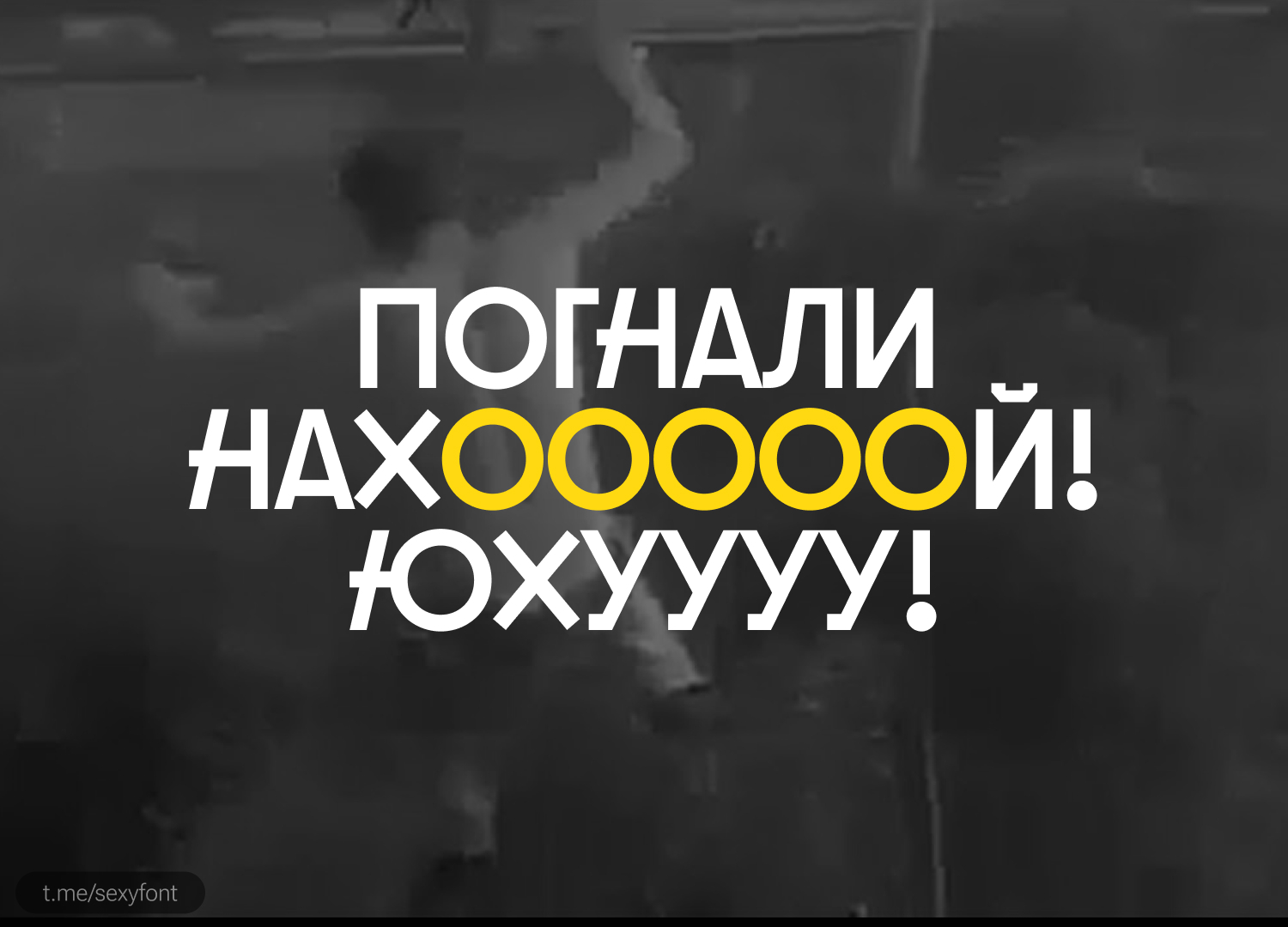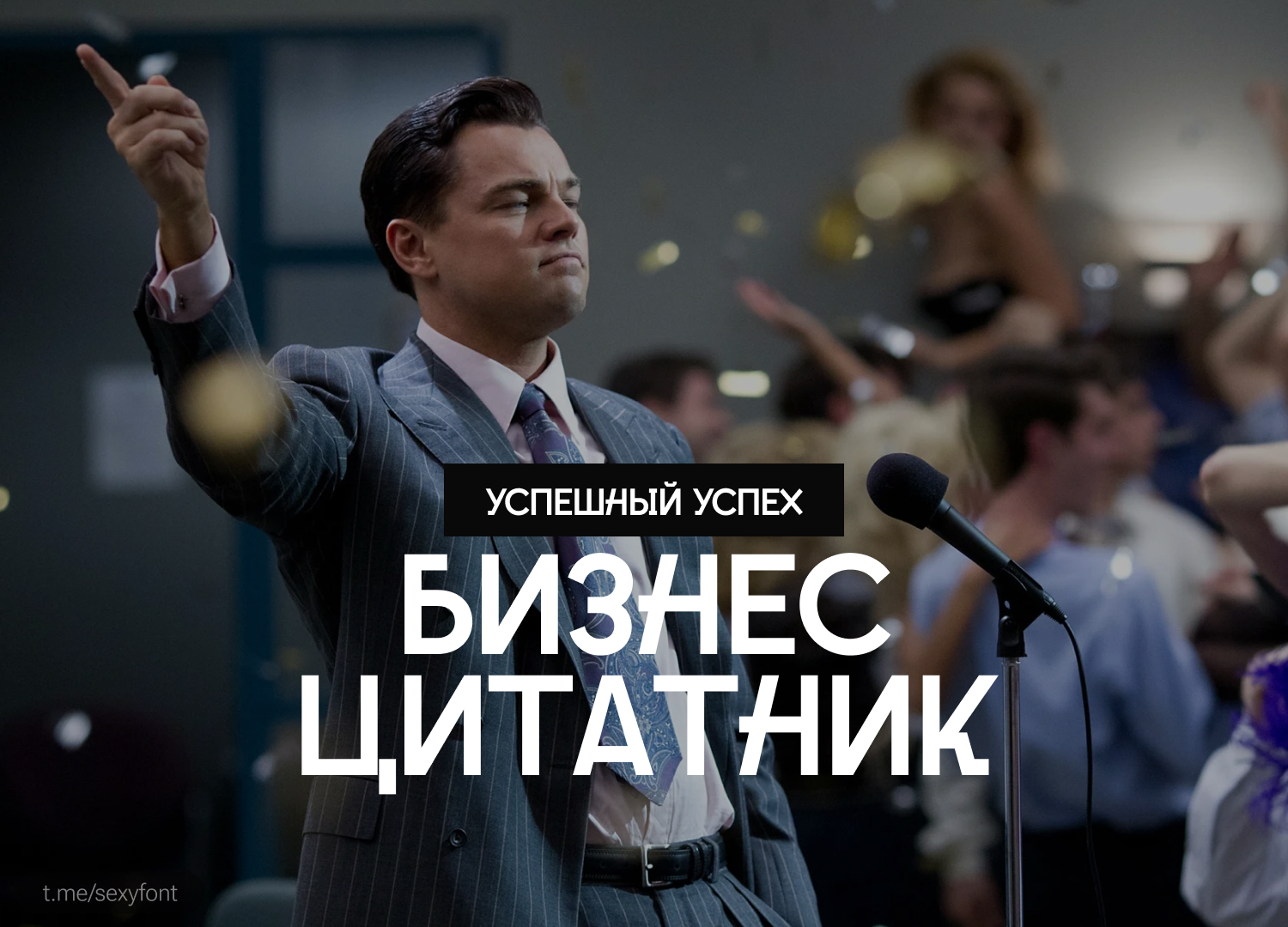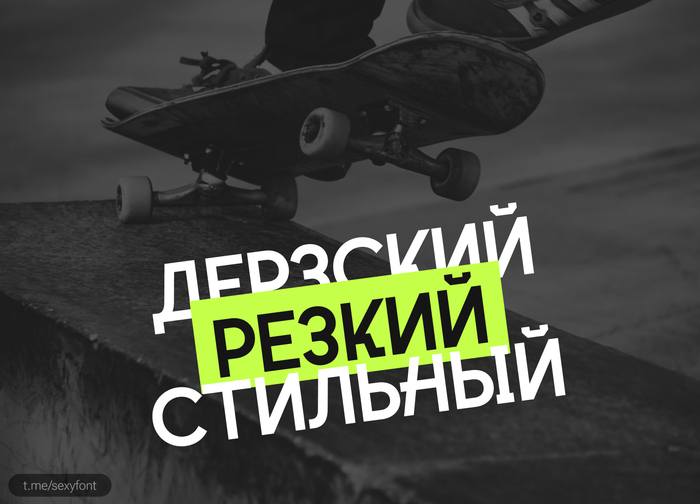
Шрифт cakra. Бесплатный. Кириллица
Cakra. Свежий, дерзкий, стильный, молодежный шрифт. Все буковки хорошо видны в презентации. Автор: OoM Type. Бесплатно для всего.